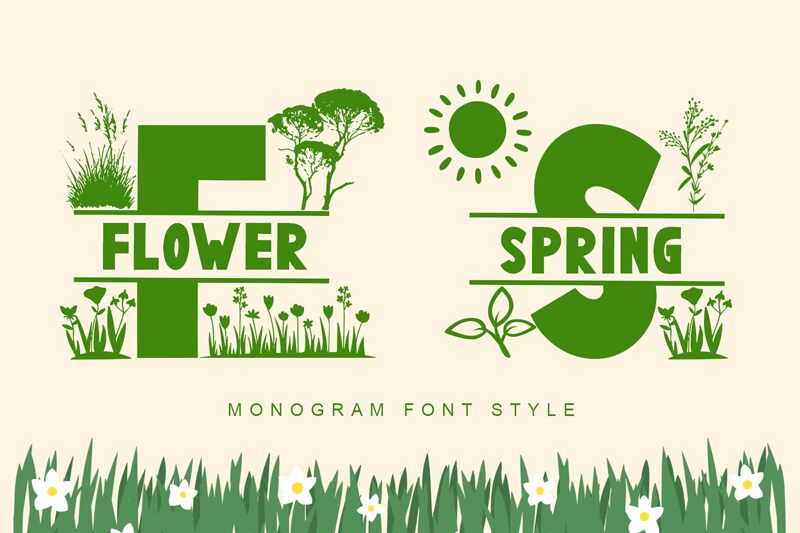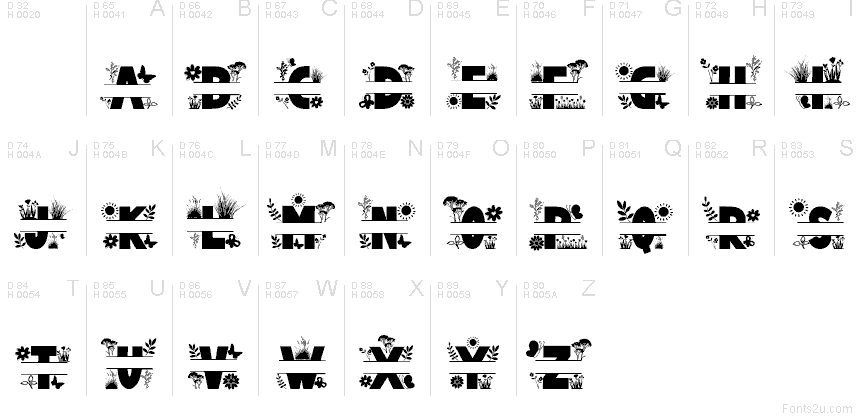
Flower Spring Monogram Only
Flower Spring Monogram Only par Yoga Letter est une police de caractères ornementale gratuite sur le thème du printemps. Elle encadre vos initiales d'herbes, de tulipes et de silhouettes végétales, utilisant des formes simples pour créer une mise en page de monogramme au rendu artisanal et saisonnier.
Flower Spring Monogram Only est parfaite pour les invitations de mariage, les cartes de fêtes au jardin, la papeterie, les badges nominatifs et les logos nécessitant un entourage floral autour des initiales. Grâce à ses motifs botaniques répétitifs, cette police gratuite transforme vos monogrammes en véritables éléments décoratifs, ce qui la rend idéale pour les étiquettes, les publications sur les réseaux sociaux et vos projets de branding saisonnier.